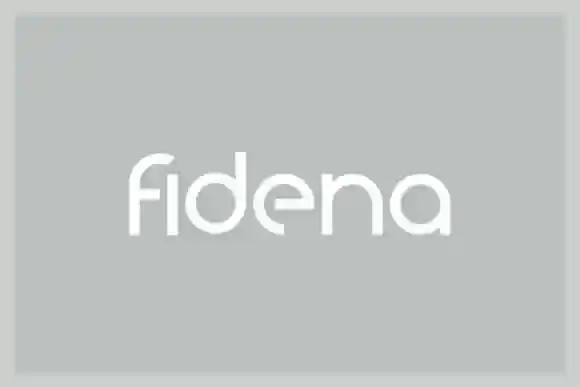
Fidena Sans Serif Font – Download Grátis
A Fidena Sans Serif é uma fonte geométrica e moderna com linhas levemente curvas que transmitem elegância mas não abrem mão da simplicidade atraente. Este conjunto de fontes percorre diversas aplicações, desde design gráfico até layouts digitais, graças ao seu estilo limpo e intuitivo. Não importa o tipo de projeto ou ocasião, a Fidena tem o potencial de se tornar sua escolha preferida para destacar qualquer mensagem ou design visual. Seja para um site de varejo, uma capa de livro impresso ou até mesmo um cartaz em um evento, a Fidena está aqui para oferecer uma combinação única e elegante entre a simplicidade geométrica da fonte e o toque delicado das linhas levemente curvadas.